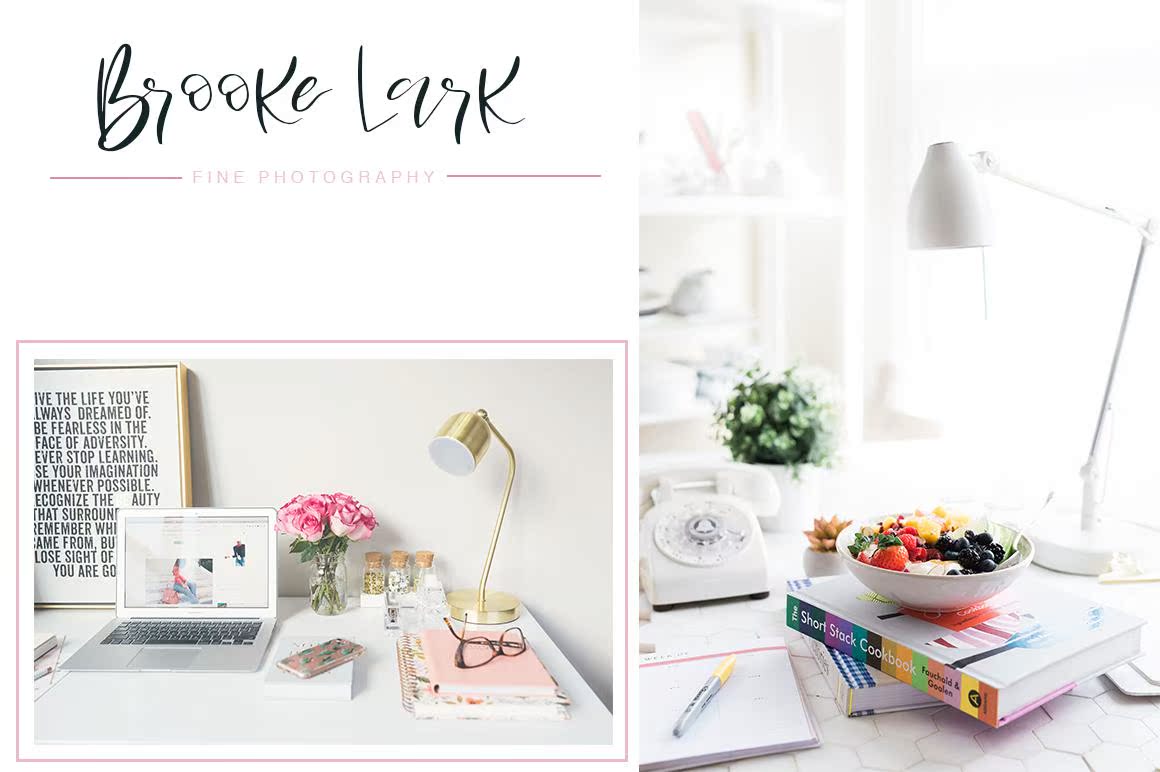
完美地为您的文字项目和品牌添加优雅和独特的触感。每个单独的文字都经过精心设计,使您的文字看起来美丽。使用文字样式,此字体将完美地形成任何不同的项目:报价、博客标题、海报、婚礼、品牌、标志、时尚、服装、信函、邀请、文具、,等。完美地为您的文字项目和品牌添加优雅和独特的触感。每个单独的文字都经过精心设计,使您的文字看起来美丽。使用文字样式,此字体将完美地形成任何不同的项目:报价、博客标题、海报、婚礼、品牌、徽标、时尚、服装、信函、邀请、文具等。